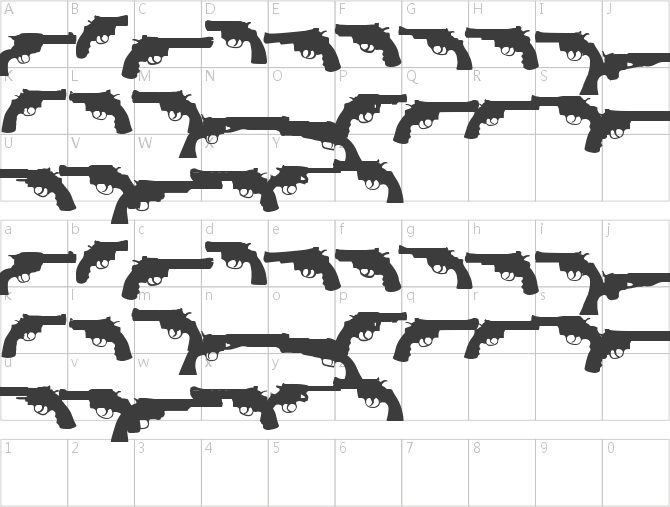
only-revolver-tfb 詳情頁(yè)
only-revolver-tfb字體字庫(kù)是一款讓人賞心悅目、百看不厭的英文字體,適合各類廣告和產(chǎn)品包裝設(shè)計(jì)應(yīng)用,字體大小0.03MB,格式為ttf字體,上傳用戶是gagilang,作者/版權(quán)方為未知